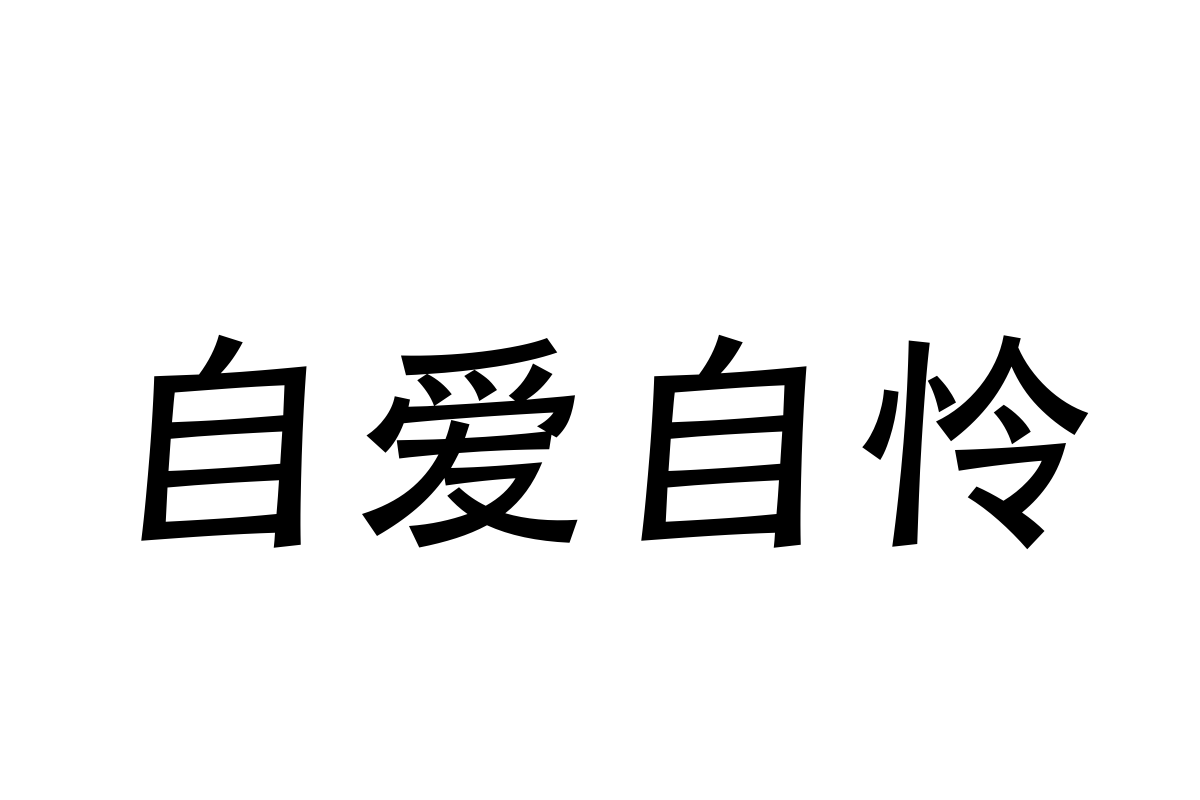
汉仪瑞云袖舞 55W是一款现代风格的中文字体,具有独特的设计和风格。这款字体的特点在于其流畅的线条和优雅的形态,给人一种轻盈、飘逸的感觉。它的笔画粗细适中,既有力量感又不失柔和,适合用于需要强调文字美感的场景。
该字体适用于广告设计、包装设计、网页设计等多种场合,能够为作品增添一份独特的魅力。无论是在视觉传达上还是情感表达上,汉仪瑞云袖舞 55W都展现出了其独特的优势。